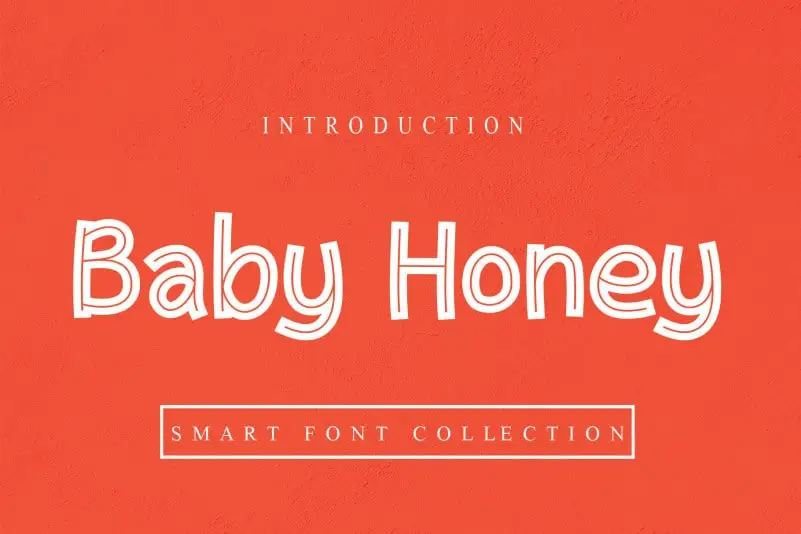
Na categoria de fontes ornamentais, a ‘Baby Honey Display Font’ oferece uma experiência visual única para qualquer projeto que precise de um toque especial. Desenvolvida pelo designer creativeletter, essa fonte é perfeita para criar efeitos memoráveis em designs gráficos como logotipos, materiais de marketing ou até mesmo design editorial. Suas linhas delicadas e suas cores suaves criam uma atmosfera encantadora e acolhedora que se ajusta perfeitamente ao estilo retrô e vintage. A ‘Baby Honey Display Font’ é mais do que apenas um recurso gráfico; ela oferece a oportunidade de trazer vida à sua marca ou projeto, deixando seu público olhando com admiração para as criativas expressões visuais apresentadas. Seja você criando o próximo hit de logotipo ou revolucionando uma página web convencional, a ‘Baby Honey Display Font’ está aqui para ajudá-lo a alcançar o destaque que merece em qualquer projeto.